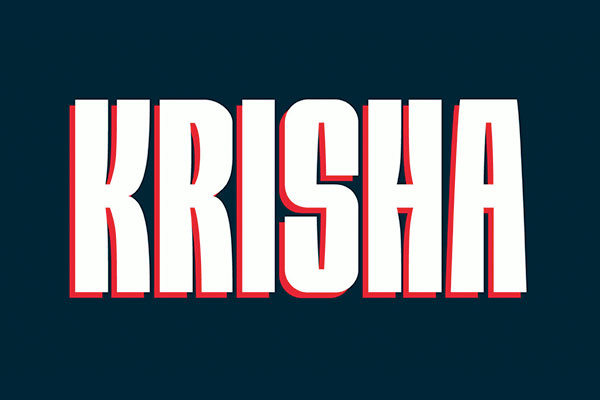
KRISHA
KRISHA字体介绍
KRISHA是美国设计师 Daler Mukhiddinov创作的一款英文字体,KRISHA拥有大粗体英文字形,适合用于海报、标题等场合。
KRISHAd的字母部分全部都是大写显示字体。字符包含大写字母,数字,符号,并且是多语言的。Krisha非常适合使任何所需的项目脱颖而出,它非常适合于海报,标题,标题,服装等。KRISHA字体首发于Pixelsurplus,遵循Open Font License (OFL)开放字体协议,免费供个人和商业用途使用。
KRISHA字体应用示例